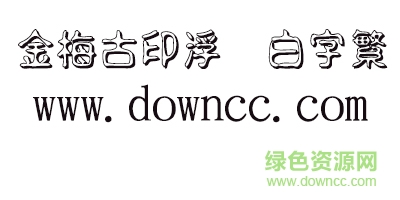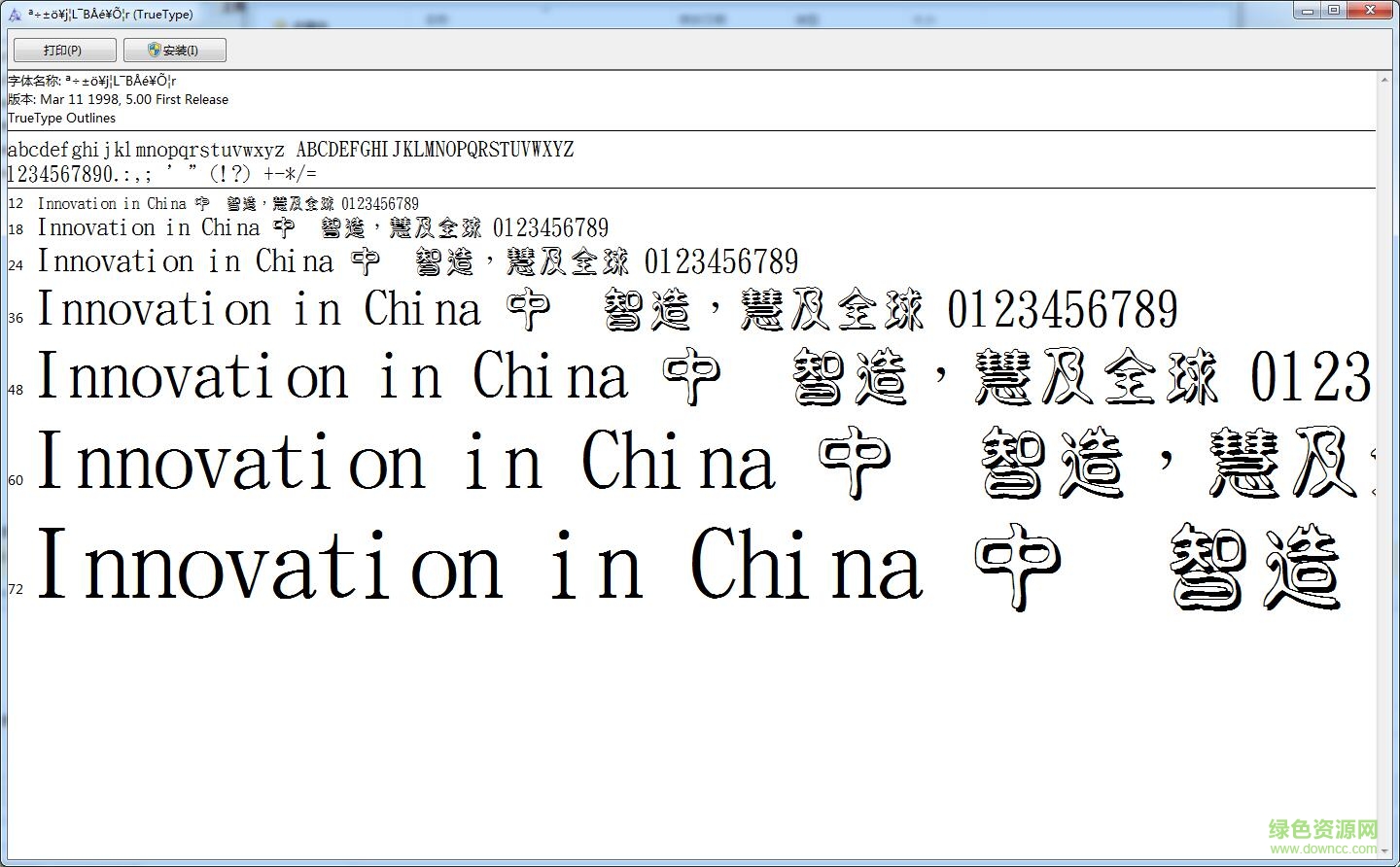
古印浮體白字繁體字體風(fēng)格非常有特點(diǎn),這款字體外形看起來像浮雕一樣,看似空洞實(shí)則比較飽滿!古印浮體白字繁字體在設(shè)計(jì)行業(yè)使用到的比較多!喜歡的用戶快來下載吧。
金梅古印浮體白字繁體是一款外表美觀的免費(fèi)字體。繁文多適用于文檔編輯、排版使用。這款字體輸出的文字非常好看!歡迎來綠色資源網(wǎng)下載使用。